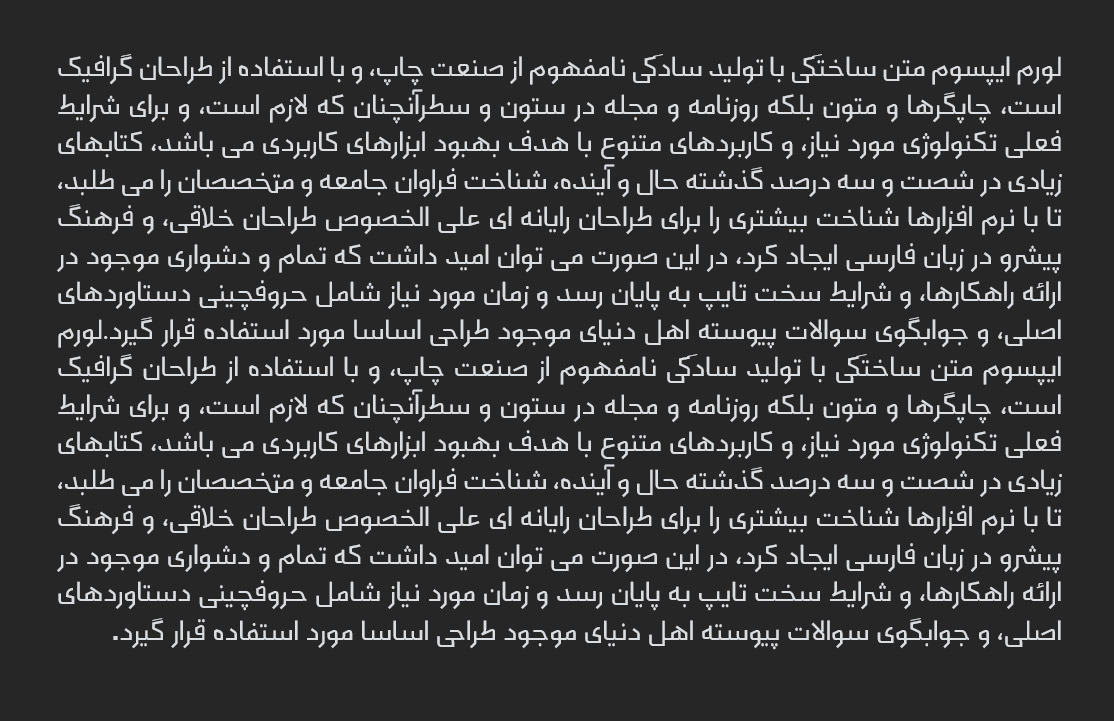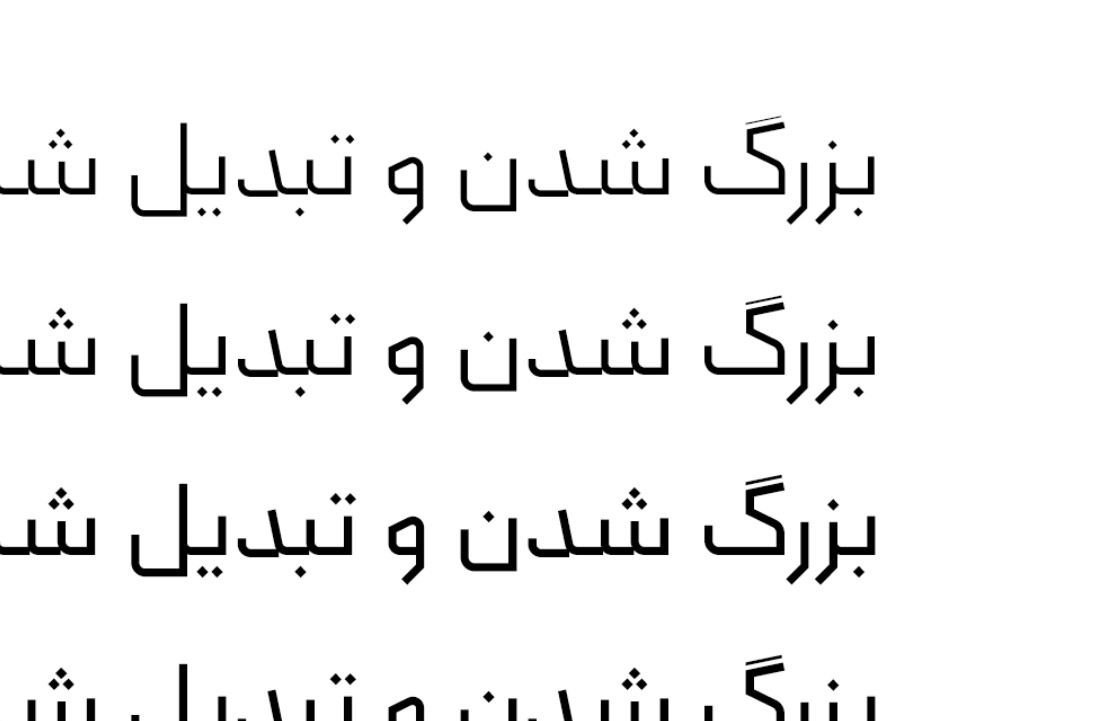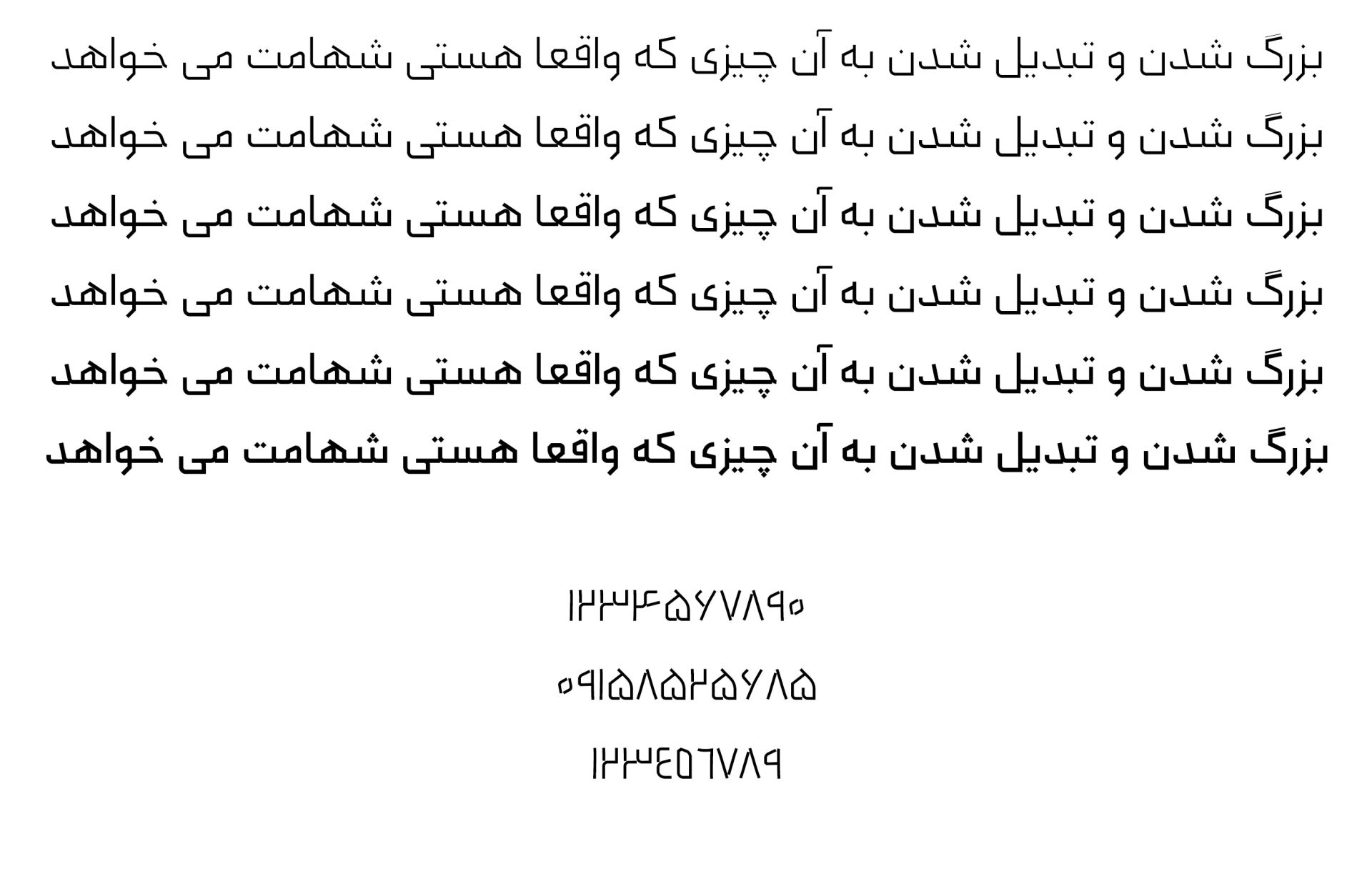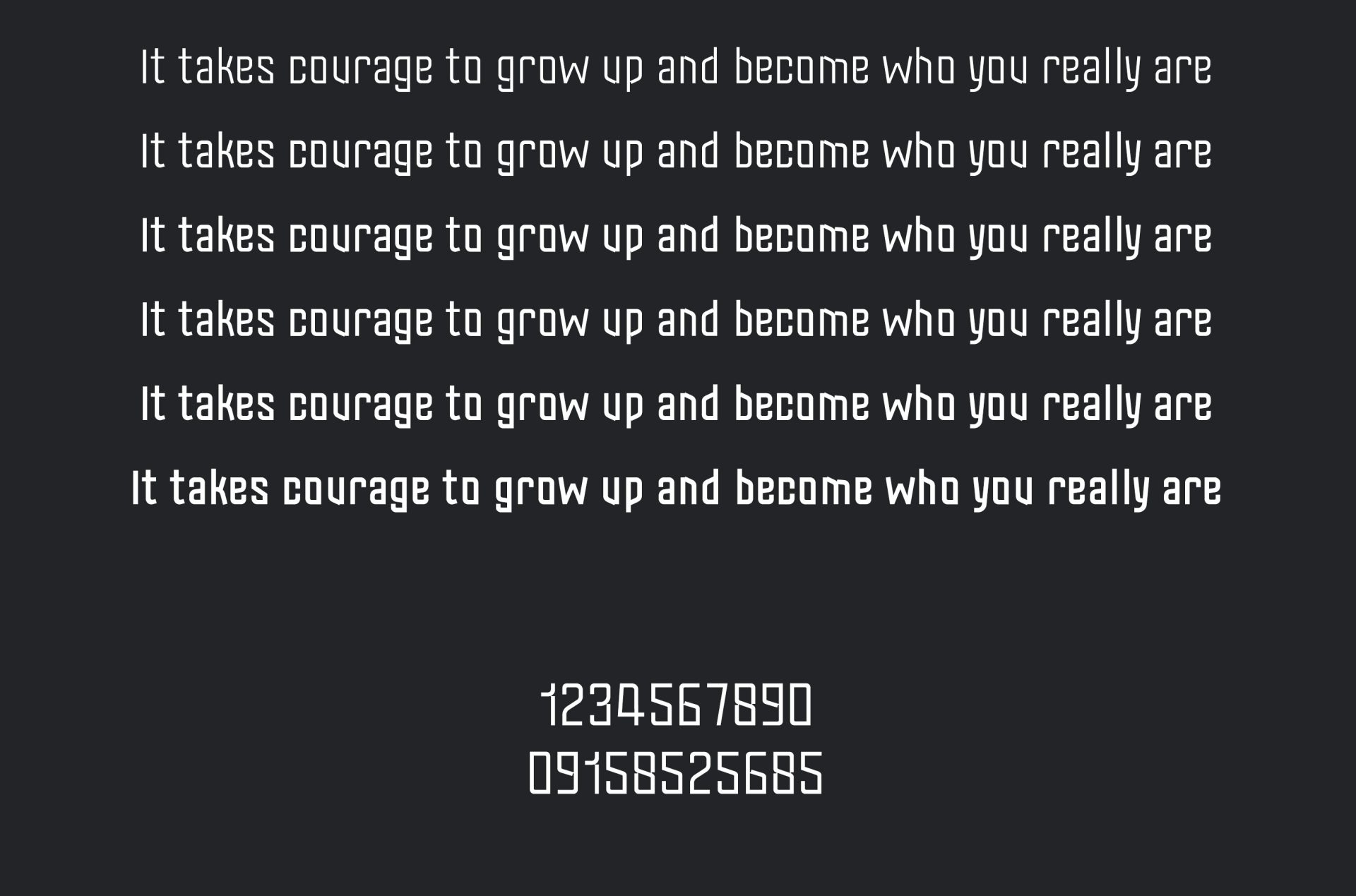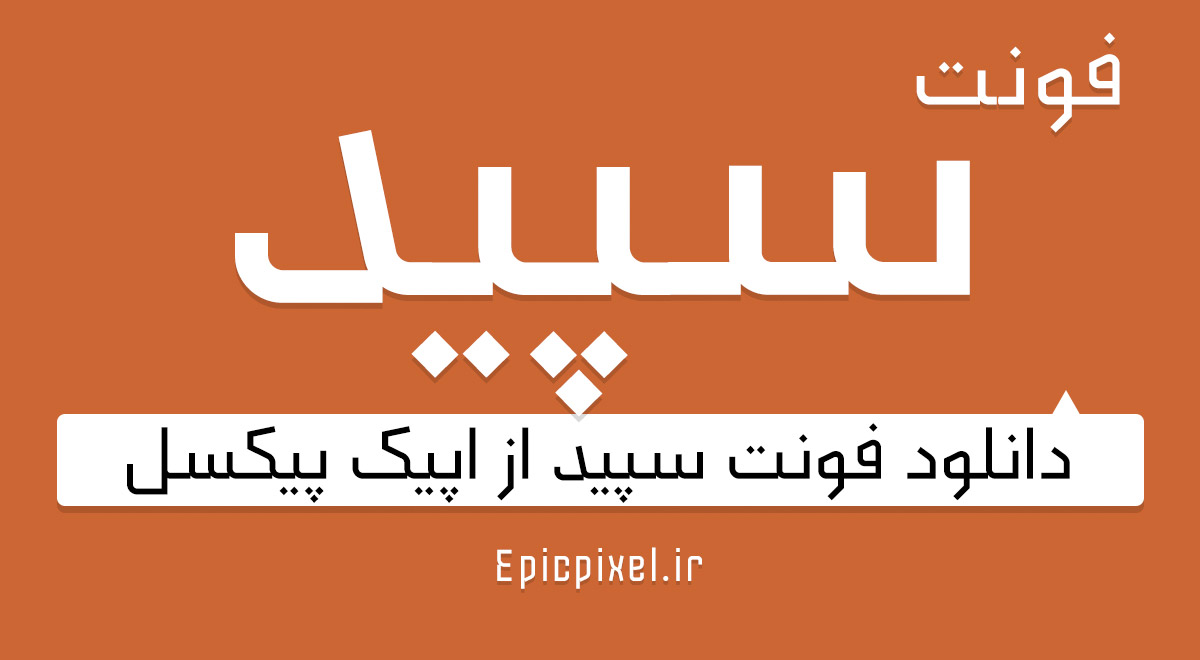
فونت سپید، با ظاهری مدرن و هندسی، انتخابی ایده آل برای کسانی است که به دنبال تایپوگرافی خاص و چشم نواز هستند. این فونت، با وجود ساختار مدرن خود، ریشه هایی در خوشنویسی سنتی ایرانی دارد و همین تلفیق، به آن هویتی منحصربه فرد بخشیده است.
یکی از ویژگی های برجسته سپید، تنوع وزن های آن است. این فونت در هفت وزن مختلف ارائه می شود که به شما امکان می دهد از آن در طیف وسیعی از کاربردها، از عناوین کوتاه و جذاب گرفته تا متن های طولانی تر، بهره ببرید. این تنوع، دست شما را در طراحی های مختلف باز می گذارد و به شما کمک می کند تا به بهترین شکل، پیام خود را منتقل کنید.
سپید، با وجود ظاهر مدرن، خوانایی بسیار خوبی دارد. طراح این فونت، با دقت فراوان، به جزئیات حروف پرداخته و تعادلی مناسب بین زیبایی و خوانایی ایجاد کرده است. این ویژگی، سپید را به گزینه ای مناسب برای استفاده در وب سایت ها، کتاب ها، مجلات و سایر رسانه ها تبدیل می کند.